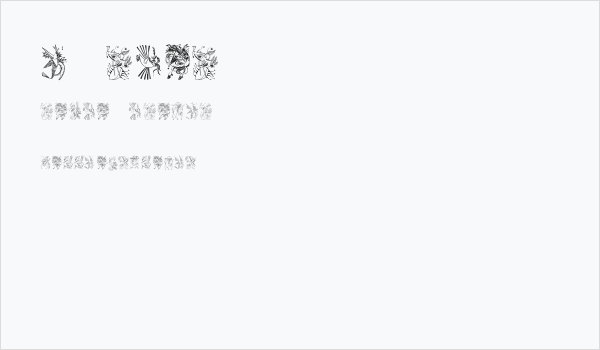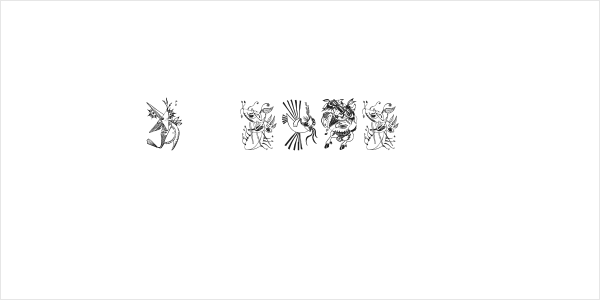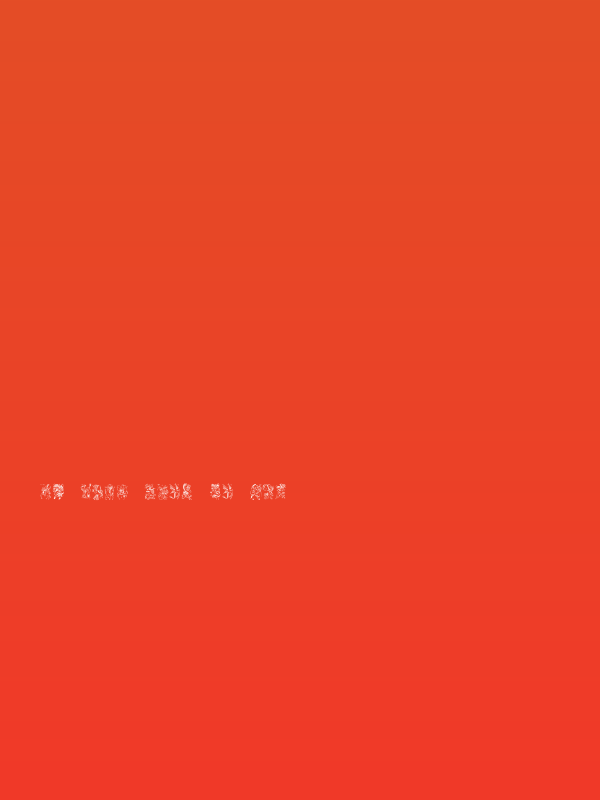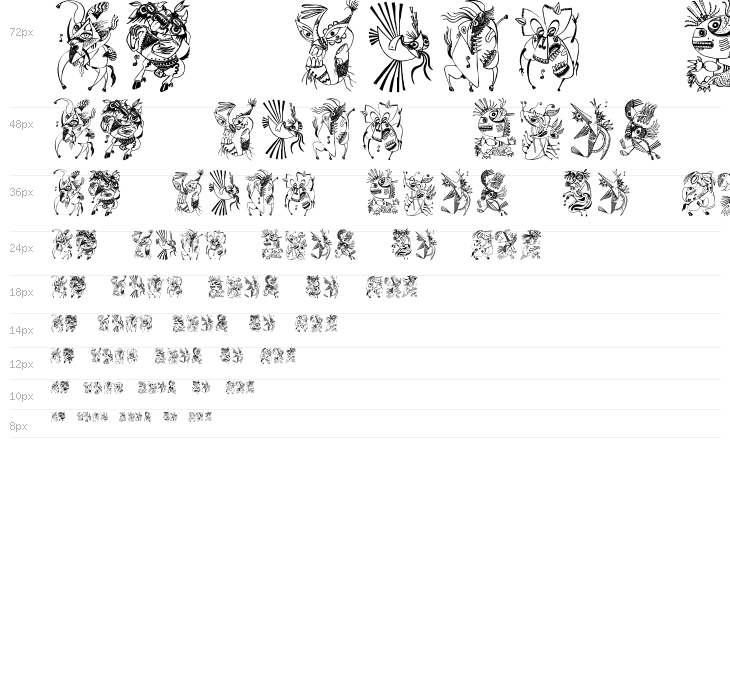
Z-Most Critter 2 Font
| Caso d'uso | Artistic elements, Illustrations, Fantasy themes |
| Progetti proposti | Ideal for creative projects such as children's book illustrations, fantasy-themed posters, and artistic branding materials. |